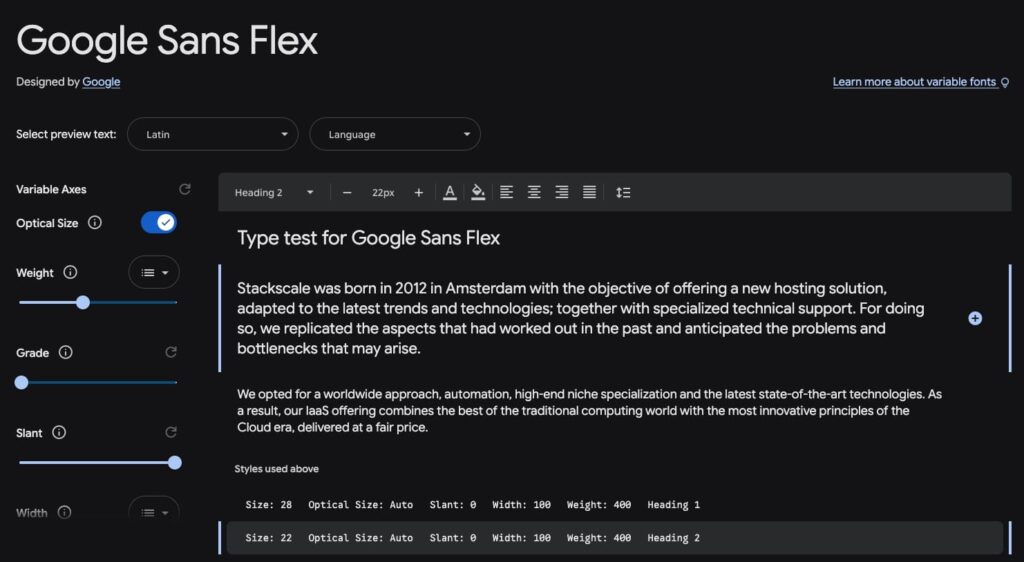
Google ha decidido abrir uno de sus activos de diseño más recientes: Google Sans Flex, una fuente open source que ya apunta a convertirse en referente para interfaces, webs y sistemas operativos que busquen una tipografía adaptable y optimizada para pantalla.
Una sola fuente, muchos estilos: el poder de las variable fonts
Google Sans Flex no es “otra sans más”. Está diseñada como fuente variable, es decir, un único archivo que concentra múltiples estilos y variaciones. En lugar de tener 10, 20 o 30 archivos distintos (Light, Regular, Medium, Bold, Condensed, etc.), aquí hablamos de un solo fichero que lo hace todo.
Según la documentación de Google, Sans Flex incluye cinco ejes de variación principales:
- Weight (peso): delgado, regular, negrita y todo lo intermedio.
- Width (anchura): más compacta o más ancha según la interfaz o el espacio disponible.
- Optical size (tamaño óptico): ajusta la forma de las letras según el tamaño al que se muestran para mejorar la legibilidad.
- Slant (inclinación): equivalente a cursiva, pero controlada de forma continua.
- Rounded terminals (extremos redondeados): permite un acabado más suave o más recto según el tono visual que se busque.
Para el usuario final esto se traduce en algo simple: la misma familia tipográfica puede verse “seria y corporativa” o “amable y redondeada” sin cambiar de fuente, solo moviendo parámetros.
Pensada para el escritorio… y más allá
Google ha diseñado Sans Flex con un objetivo claro: que funcione bien en:
- Interfaces de escritorio y móviles.
- Sistemas modernos con escalado fraccionado.
- Pantallas de alta densidad (HiDPI/Retina).
Esa combinación de variable font + optimización para pantalla tiene varias ventajas prácticas:
- Menos fatiga visual en entornos de trabajo intensivo (IDE, navegador, terminal, paneles de administración).
- Renderizado más nítido al combinar tipografía y escalado no entero.
- Mayor consistencia entre distintas plataformas, algo clave para productos que viven a la vez en web, Android, iOS y escritorio.
Para quienes usan Linux y personalizan el sistema al detalle, Google Sans Flex se suma a un ecosistema donde ya brillan fuentes como Inter, Roboto, Noto o Cantarell.
Eso sí, hay un matiz importante en el escritorio Linux actual:
aunque Sans Flex sea variable, no todos los entornos de escritorio aprovechan todavía esos ejes de variación a nivel global. En muchos casos, si se aplica como fuente del sistema, el usuario verá básicamente la variante “normal”, mientras que el control fino de peso, anchura o tamaño óptico quedará reservado a:
- Apps de diseño que soporten variable fonts.
- Navegadores web modernos usando CSS (
font-variation-settings). - Editores y herramientas que entiendan estos ejes de forma explícita.
Dicho de otro modo: la fuente es completamente usable hoy, pero su verdadero potencial se disfruta mejor en flujos de trabajo de diseño y desarrollo.
Por qué importa que Google la haga open source
Que Google abra Sans Flex no es solo un gesto de PR: tiene consecuencias prácticas en el ecosistema:
- Diseñadores de UI/UX ganan una tipografía moderna, bien mantenida y con soporte a largo plazo.
- Proyectos web pueden unificar branding y legibilidad sin depender de archivos separados para cada estilo.
¿Para quién tiene más sentido Google Sans Flex?
Aunque cualquier usuario puede instalarla por curiosidad, Sans Flex tiene un encaje especialmente interesante en tres perfiles:
- Desarrolladores de producto y frontend
Que quieren un sistema tipográfico flexible en web y móvil con un único archivo de fuente. - Diseñadores de interfaces
Que necesitan adaptar densidad, tono visual y jerarquía tipográfica según dispositivo y contexto. - Usuarios avanzados de escritorio
Que personalizan GNOME, KDE o tiling WMs y buscan una fuente moderna, legible y coherente con la estética actual de Google.
Para el resto, puede ser simplemente “una buena fuente más”. Pero para quienes viven entre Figma, VS Code, navegadores y terminales, es una pieza más de un escritorio afinado.
Preguntas frecuentes sobre Google Sans Flex
¿Puedo usar Google Sans Flex en proyectos comerciales?
Sí. La fuente está publicada bajo licencia SIL Open Font License, lo que permite su uso en proyectos comerciales y de código abierto, respetando las condiciones de la licencia.
¿Las características variables funcionan en todos los escritorios Linux?
No siempre. Muchos entornos aún tratan las fuentes variables como una fuente “normal” cuando se usan a nivel de sistema. Para explotar los ejes de variación suele hacer falta software compatible (navegadores modernos, apps de diseño, etc.).
¿Sustituye a fuentes como Roboto o Inter?
Depende del caso de uso. Sans Flex puede convivir con ellas. Para proyectos nuevos o productos que quieran un look alineado con el diseño actual de Google, sí puede ser una alternativa muy interesante.